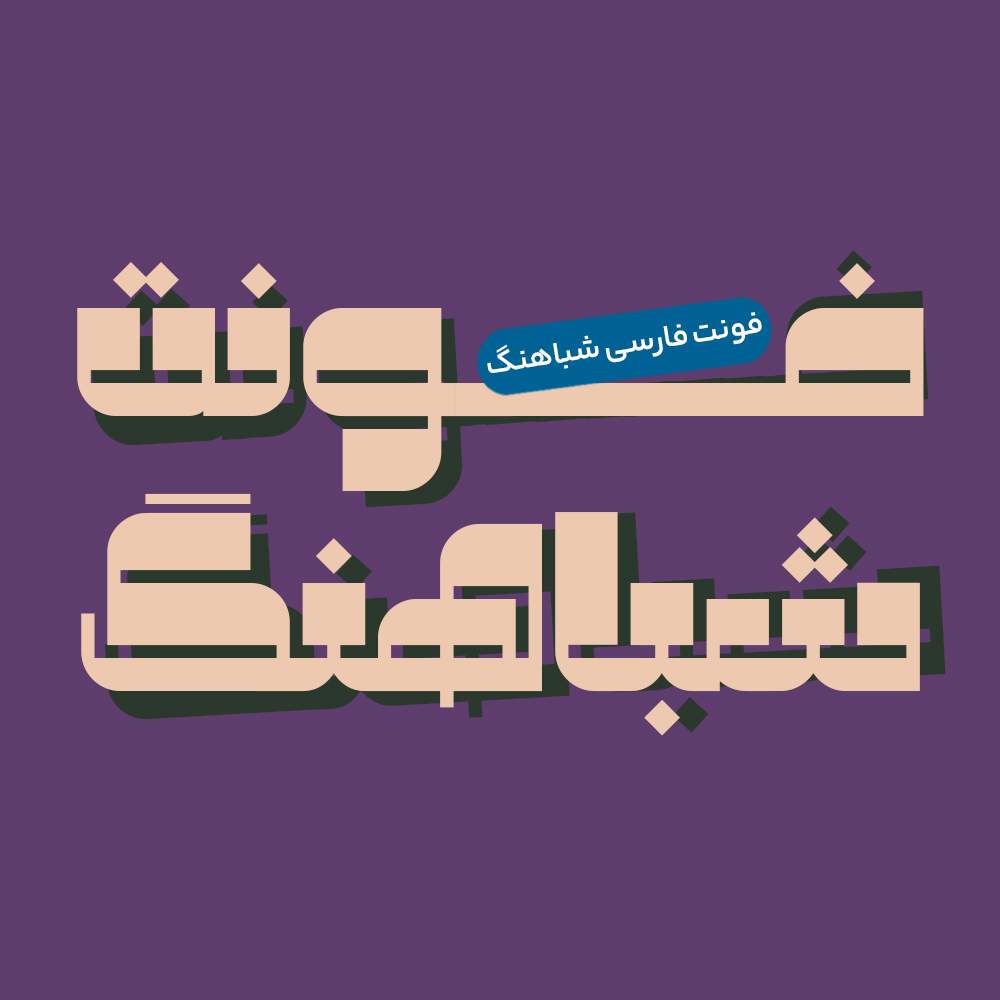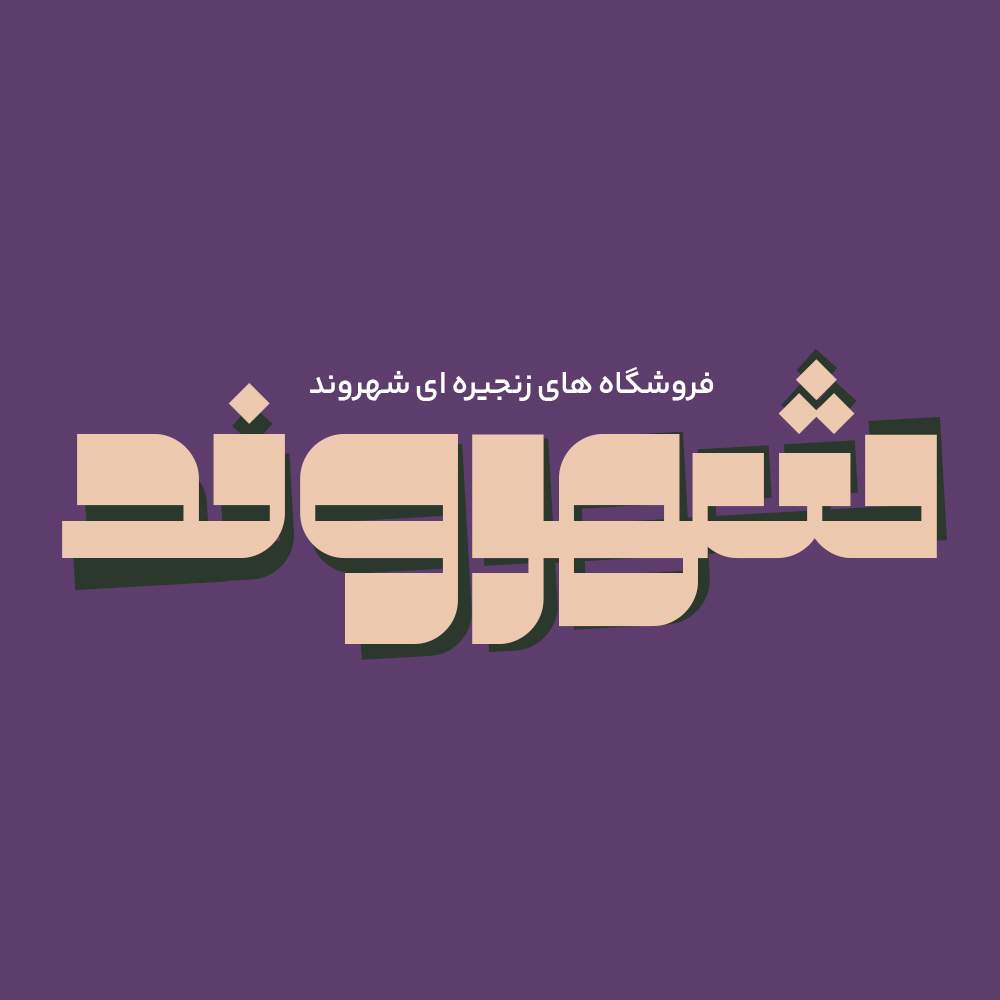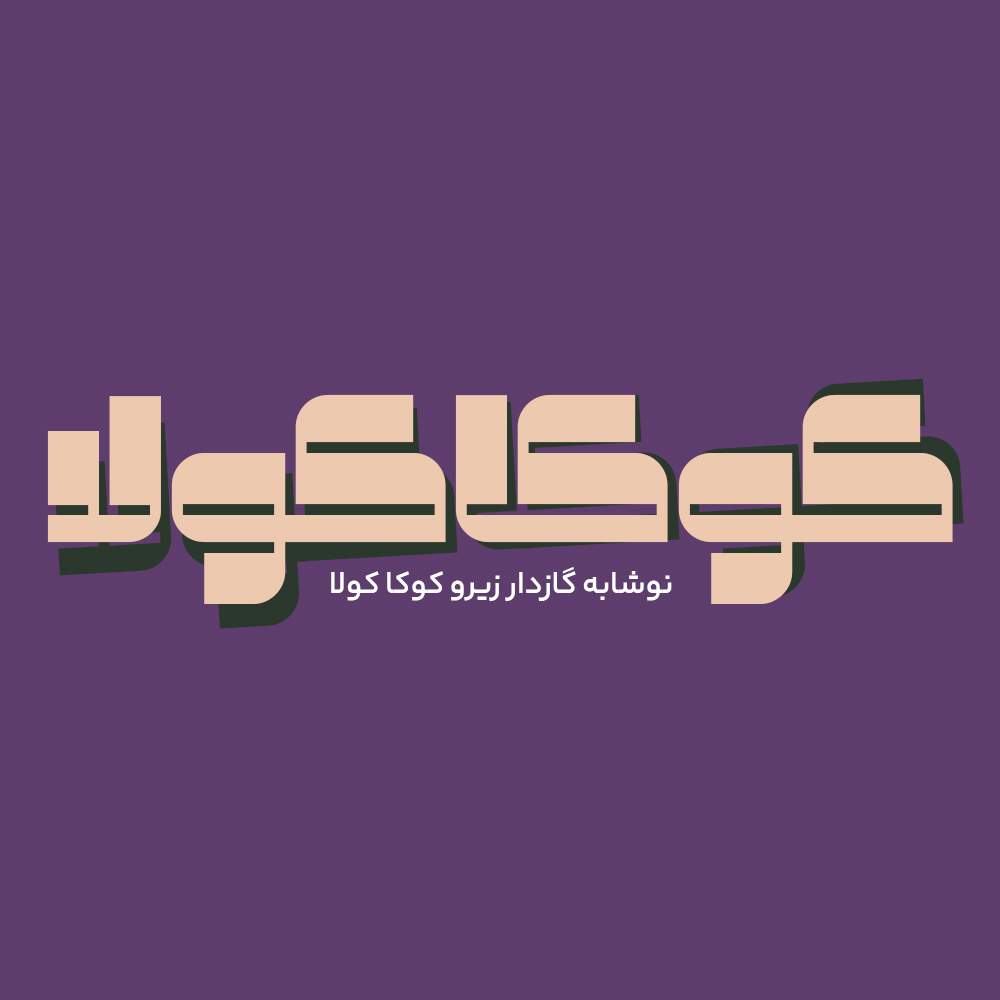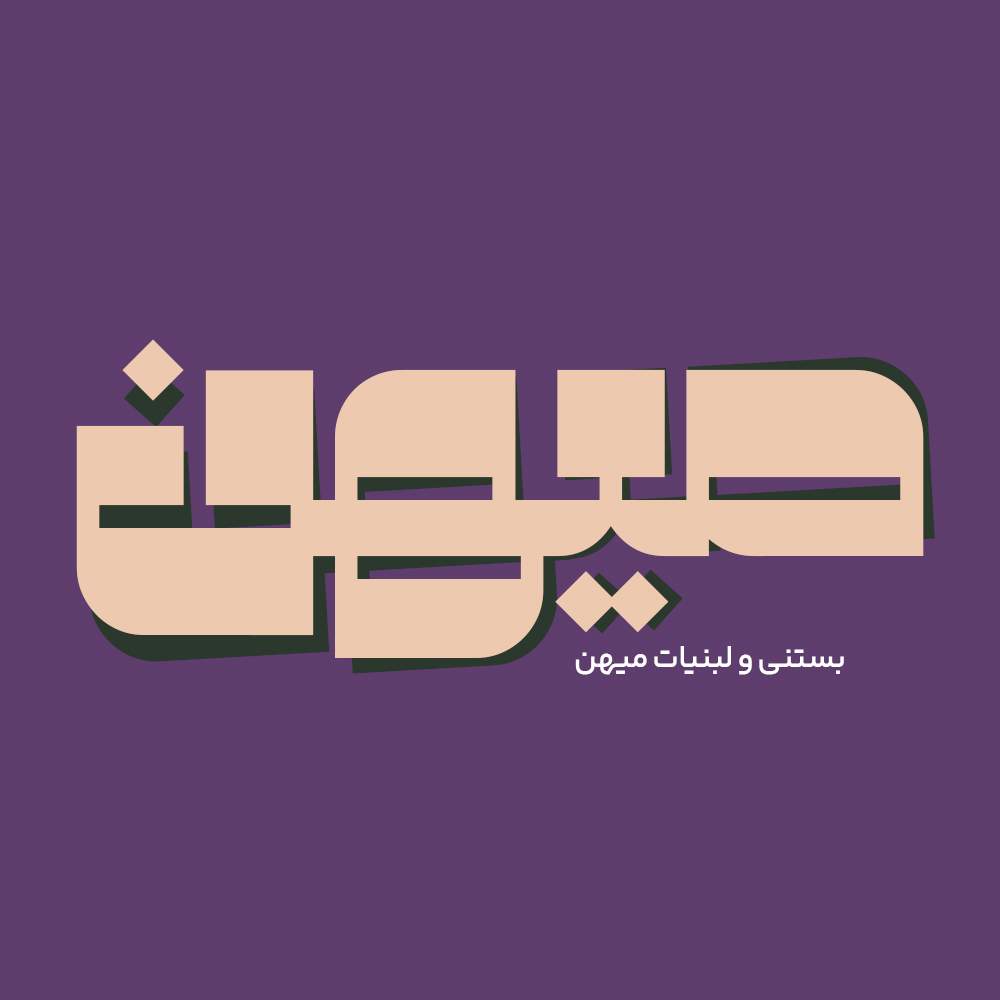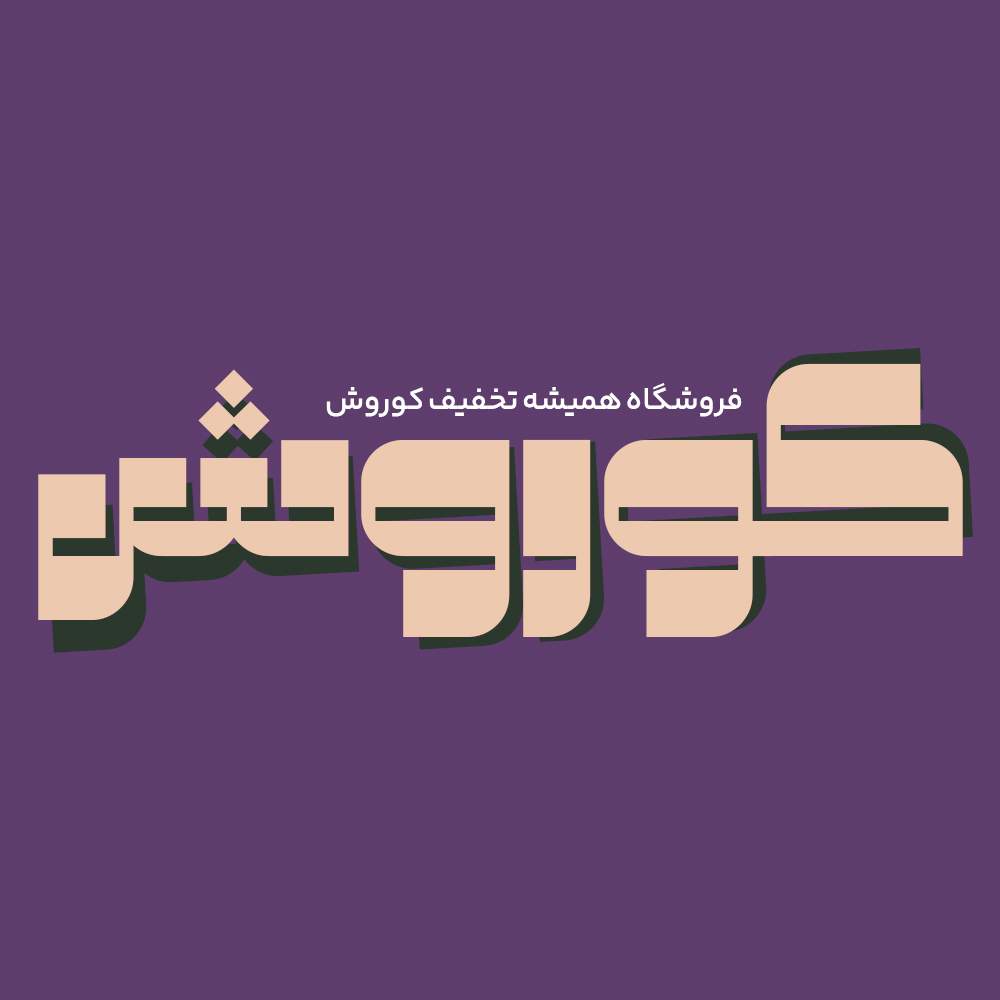
فونت فارسی شباهنگ یک فونت متفاوت و زیبای فارسی میباشد که در وزن بولد طراحی شده است و با طراحی و سبک خاصی که دارد از سایر فونتهای این سبک متفاوت میباشد، این فونت زیبا در عین سادگی که فونت های بسیار سنگین دارند یک طراحی خاص دارد که سبب متفاوت شدن و هنری تر شدن این فونت میشود و مناسب انواع طراحی گرافیکی می باشد.
فونت شباهنگ یک فونت تک وزن با کاربرد طراحی لوگوتایپ و طراحیهای مختلف همچون کتاب و تولید محتوای متنهای کوتاه و عناوین میباشد. این فونت با ساختار حروف خود مناسب استفاده در لوگوهای نوشتاری میباشد. همچنین از این فونت در طراحی تابلوهای چلنیوم هم به دلیل ساختار منحصر به فردش میتوانید استفاده کنید. در ادامه برای شما نمونه تایپ های این محصول حرفهای رو آماده کردهایم که میتوانید مشاهده کنید.
پیشنمایش و نمونه تایپ های فونت شباهنگ